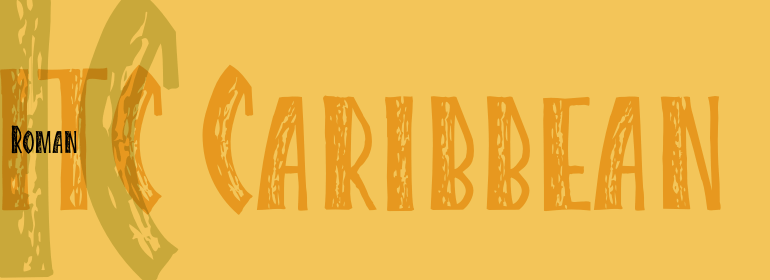
ITC Caribbean™
ITC Caribbean™,这款字体结构工整、笔画清晰,兼顾美观与易读性,适用于标题、正文、海报、包装、LOGO 等多种场景。字形优雅稳定,风格百搭耐看,适配日常排版与创意设计,让文字呈现更舒适、更具质感。ITC Caribbean™一笔一画,皆是细节,以均衡的比例、流畅的线条打造舒适视觉体验,字形端正大气,风格简约现代。无论是商业设计、品牌宣传还是日常排版,都能轻松驾驭,让文字更有格调与力量。ITC Caribbean™字体下载。
字体品牌: ITC(Monotype) 设计师:Bell,Jill 字体分类:衬线体 字体属性:外文 字符集:Unicode 发布时间: 2018